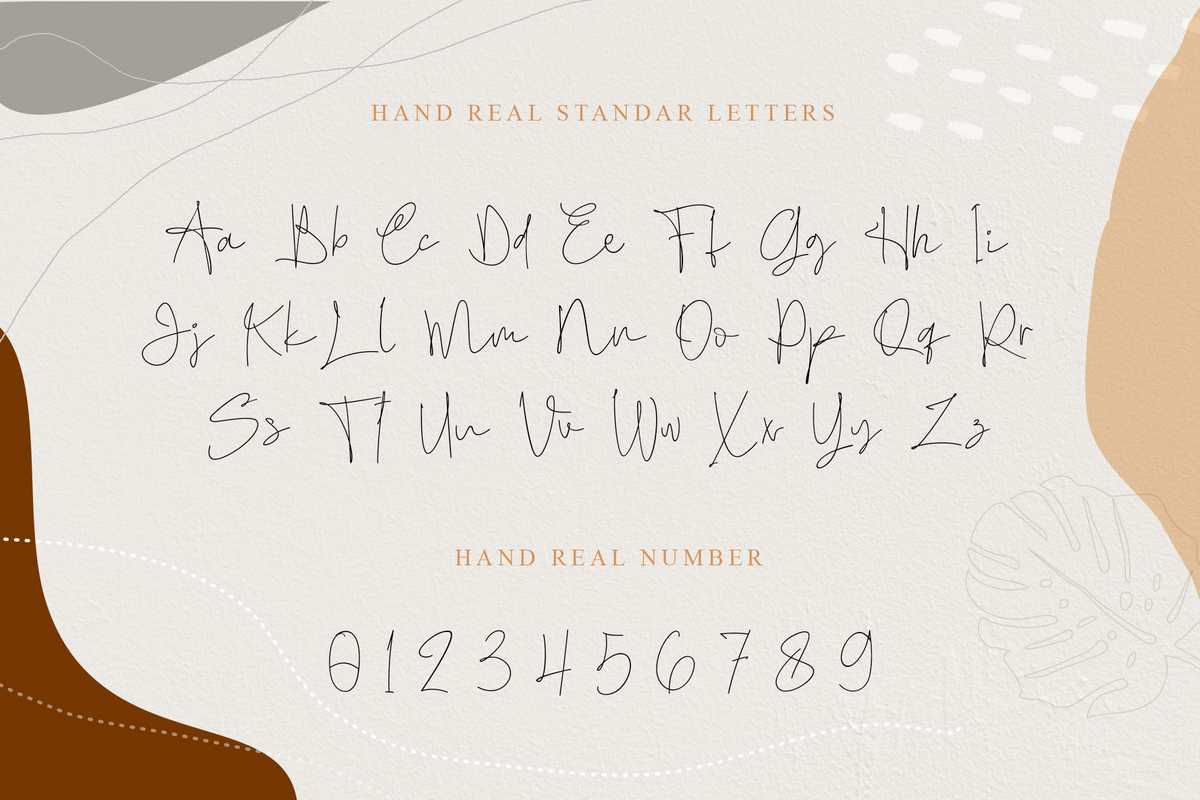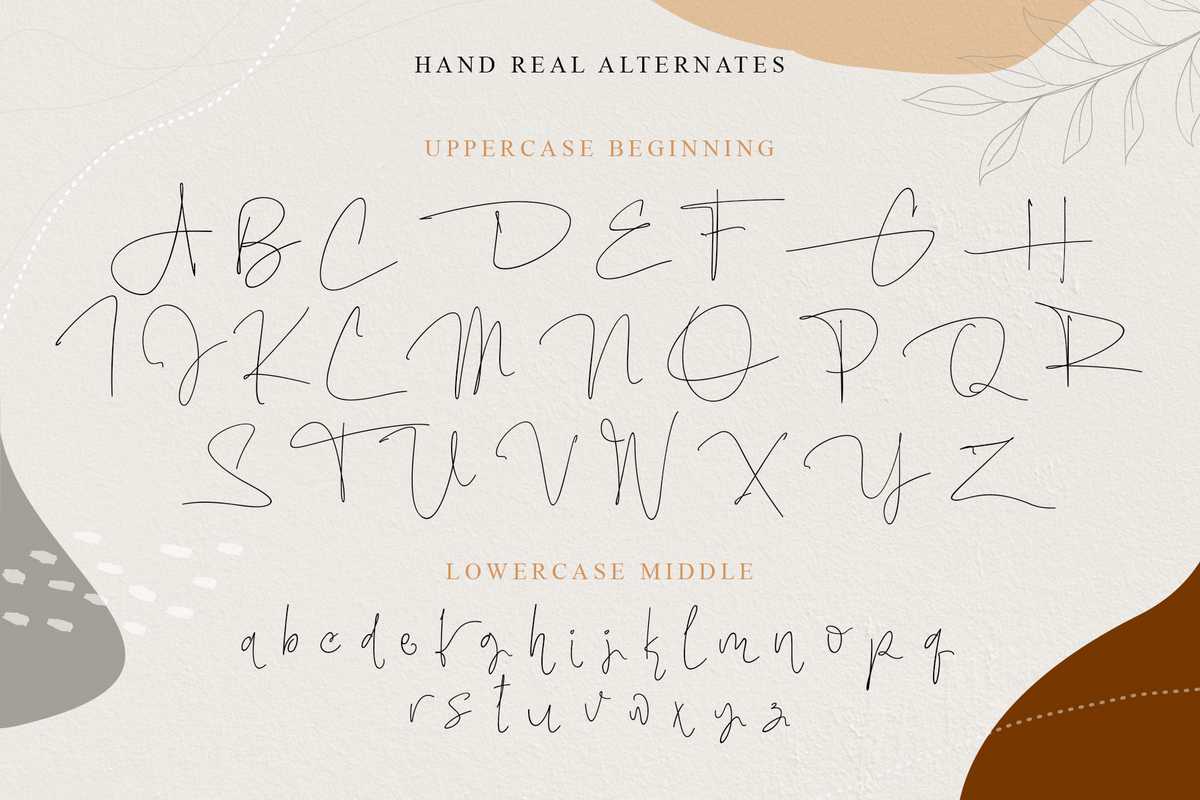
HandReal字体是由使书写更酷、更独特的符号构成的。ImpandNaturalMonolineScriptStyle适合年轻、大胆、更酷的设计。HandReal字体是由使书写更酷、更独特的符号构成的。ImpandNaturalMonolineScriptStyle适合年轻、更大胆、更宽松的设计理念。HandReal字体是由使书写更酷、更独特的符号构成的。ImpandNaturalMonolineScriptStyle适合年轻人,boldandcooldesign.HandrealFonts是女性化、喜爱和宽松概念设计的完美选择。